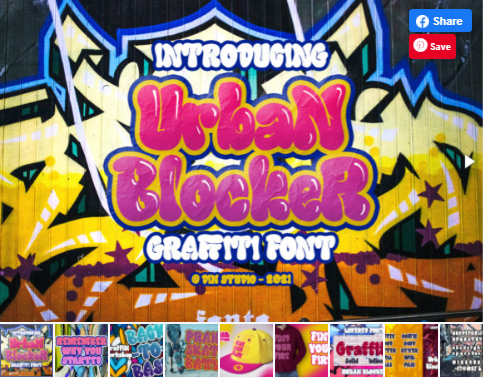
Urban Blocker Font
Urban Blocker - это крутой, свежий и модный дисплейный шрифт. Добавьте этот шрифт в стиле граффити к каждому своему городскому дизайну и воплотите его в жизнь!